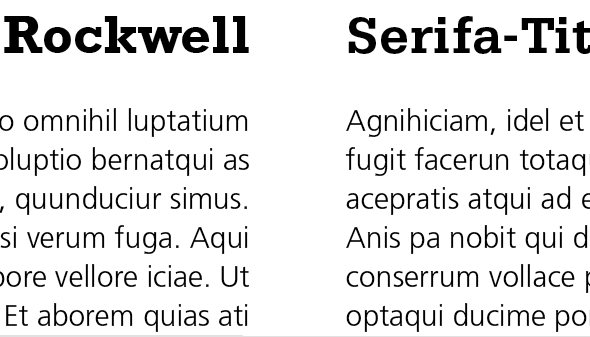
als Überschrift die Rockwell + für den Fliesstext ???
Ich muss ein Portrait über mich schreiben. Habe jetzt als Überschrift die Rockwell gewählt und beim Fliesstext die Frutiger Light...Wie findet ihr die Wahl? Ich dachte, dass zur Rockwell eine Schrift ohne Serifen geeigneter ist, als eine Schrift mit Serifen (z.B. die Minion oder Garamond)...Wäre um eine Antwort sehr dankbar.
Ja, das kann ich mir schon vorstellen dass das zusammenpasst. Vielleicht noch statt der Rockwell die Glypha nehmen, wenn du bei Frutigers Schriften bleiben möchtest (Harmonie-Garantie?), aber das klappt schon.
Details? Zeigen :)
Vielleicht noch statt der Rockwell die Glypha nehmen, wenn du bei Frutigers Schriften bleiben möchtest
Oder die Serifa, die ist etwas weniger schmal. Passt vielleicht noch besser zur Frutiger?
Dito: zeig doch mal :D so Ferndiagnosen scheinen mir immer so'n bisschen halbsinnlos.
gnff... Serifa meinte ich doch :)
:hammer: Ich mach die auch immer durcheinander. Ich gebe zu, ich hab nachgeschaut.
Danke Sebastian Nagel und NinaS für die Antworten! Habe jetzt mal auf myfonts.com bei der Serifa meinen Namen ausprobiert und muss zugeben, dass die Serifa irgendwie leichter daherkommt als die Rockwell, besonders das "A" gefällt mir besser.
Hei Andre, die Rockwell ist schon auch kuhl. Ich mag die beide ganz gern. Aber im direkten Vergleich scheint mir die Kombi mit der Serifa etwas harmonischer (siehe Anhang).
Wobei ich mich grad frage, ob dazu die Univers nicht noch besser passen würde als die Frutiger? Hmm.
Ja absolut. Besonders das schwungvolle "S" der Serifa ist sehr schön. Aber leider habe ich die Serifa nicht auf dem System...Aber habe jetzt einmal schnell mit dem Word dein Vorschlag mit der Univers umgesetzt: Die Variante eins mit Überschrift Rockwell und Frutiger, darunter die Variante eins mit Überschrift Rockwell und Univers.